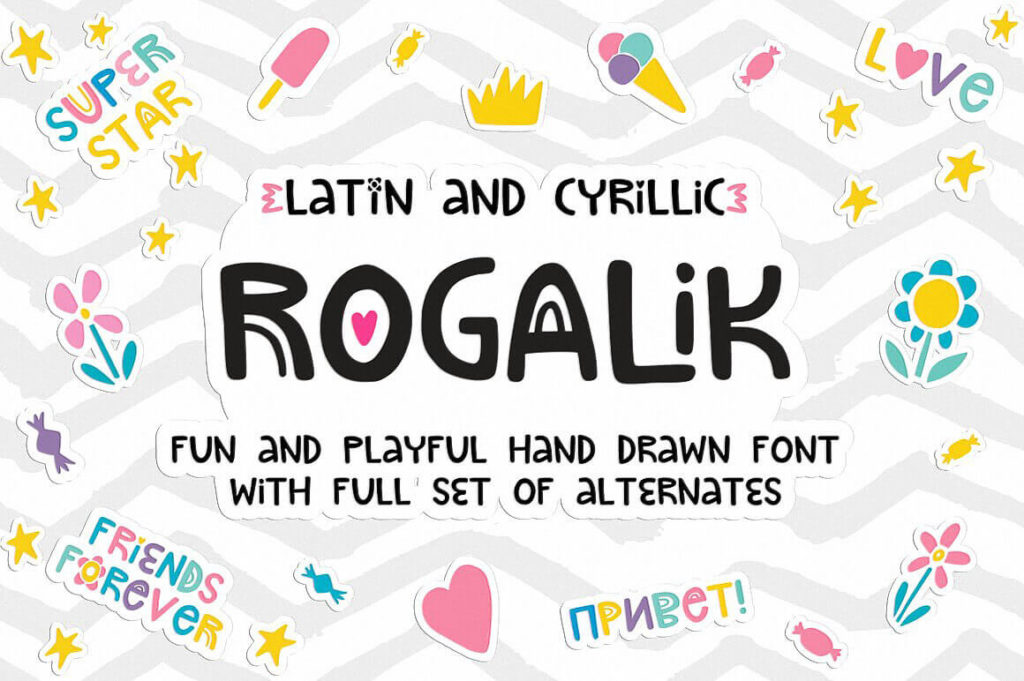
Шрифт Rogalik Hand Lettered
это игривый рукописный шрифт от студии **PicByKate**, выполненный в стиле наивного искусства. В наборе представлены заглавные буквы латиницы и кириллицы, отличающиеся характерным «детским» почерком и плавными линиями. Название шрифта вдохновлено любимыми печеньями автора («rogaliki»), что придает ему тёплое, уютное настроение. Он идеально подходит для создания позитивных визуальных образов, где важна искренность и дружелюбие. Скачать бесплатно можно только в ознакомительных целях; для коммерческого использования требуется приобретение лицензии у автора.